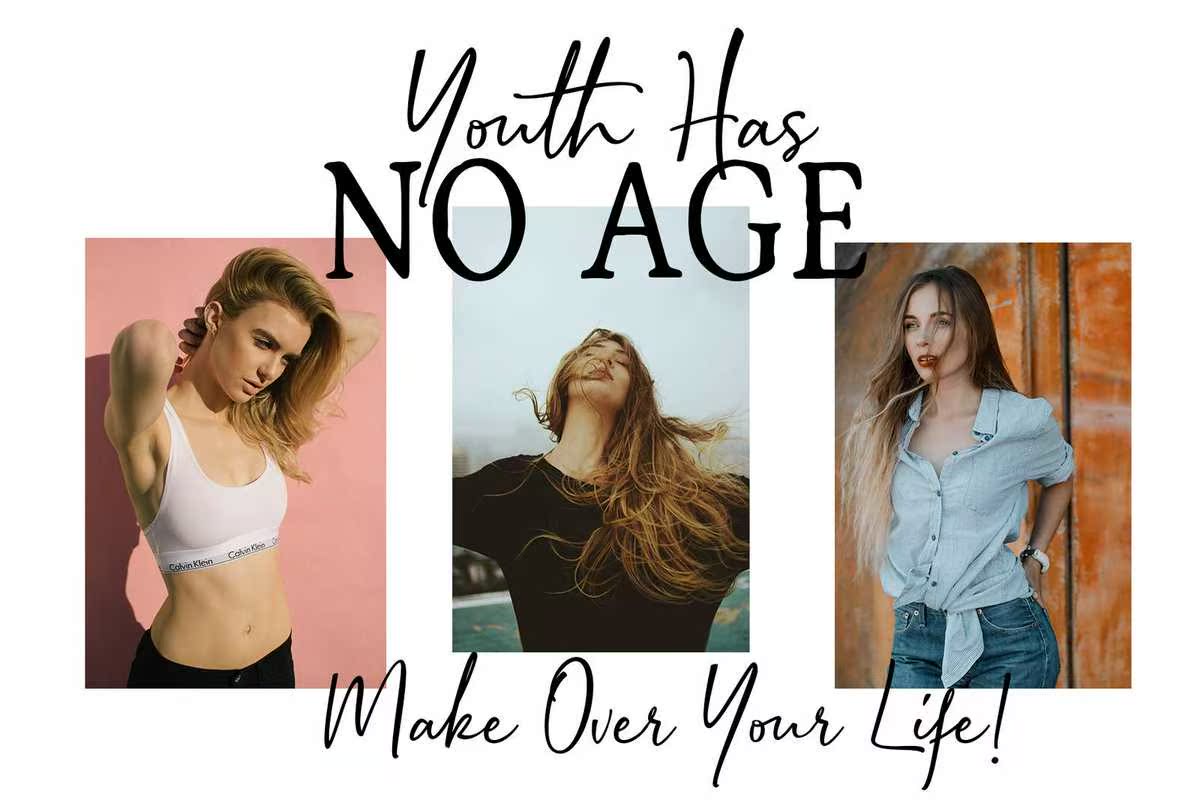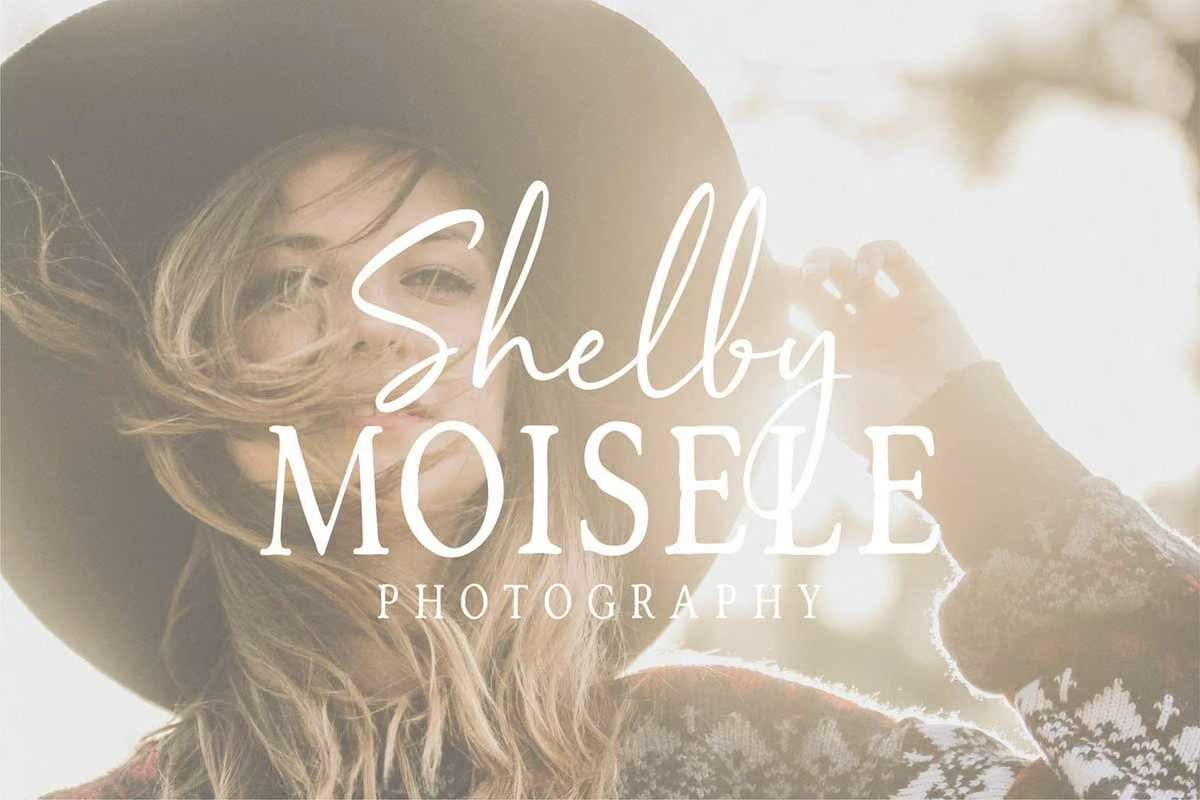
介绍由UxuryFashion激发的复杂风格字体aclassy、FunandFabolousDreamy。复杂风格包含10个完整版本的经典变体、开放式功能,包括风格替换、旋转和大规模调整。介绍复杂风格字体aclassy,FunandFaboloUSDreamyFound由UxuryFashion激发。复杂度包含10个完整版本的经典变体,开放式功能,包括不同风格的替代品、swashes和Massiveligrates。